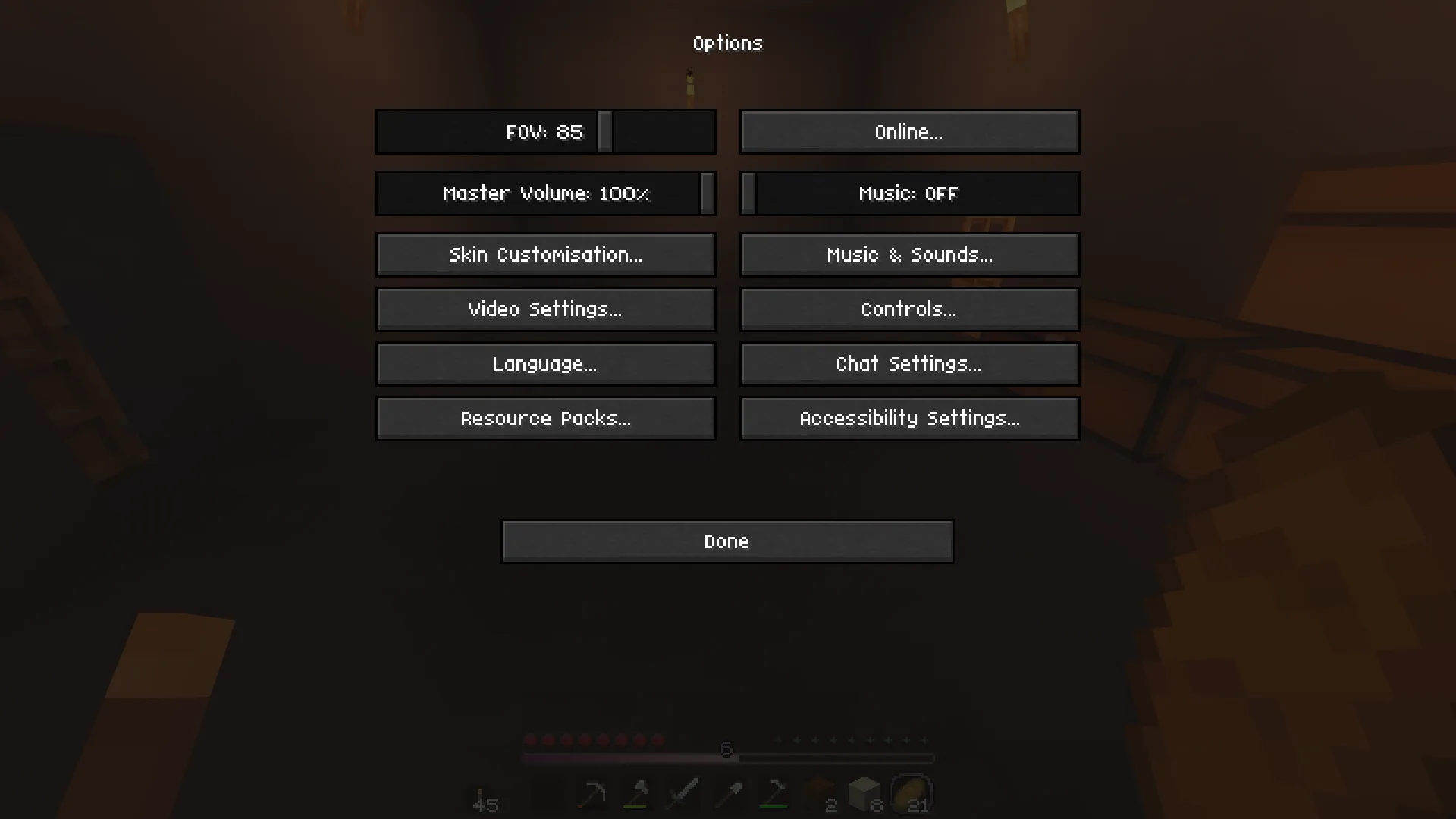
Compact Font
Компактная замена стандартного шрифта Minecraft, уменьшающая размер текста для лучшего восприятия.
Этот ресурспак предлагает компактный шрифт, который заменяет стандартный в Minecraft. Он уменьшает размер текста, делая его более удобным для чтения и экономичным по пространству на экране.
Стиль шрифта сохраняет узнаваемость оригинального дизайна, но с улучшенной компактностью, что может положительно сказаться на производительности за счёт меньшего использования ресурсов. Ресурспак совместим с указанными версиями Minecraft и фокусируется на чистом визуальном улучшении без изменения игровой атмосферы.